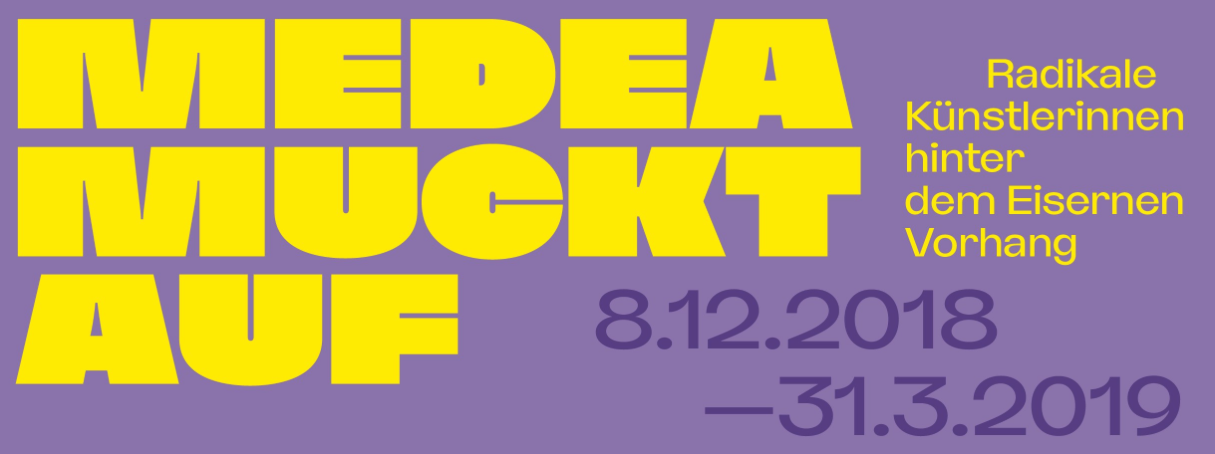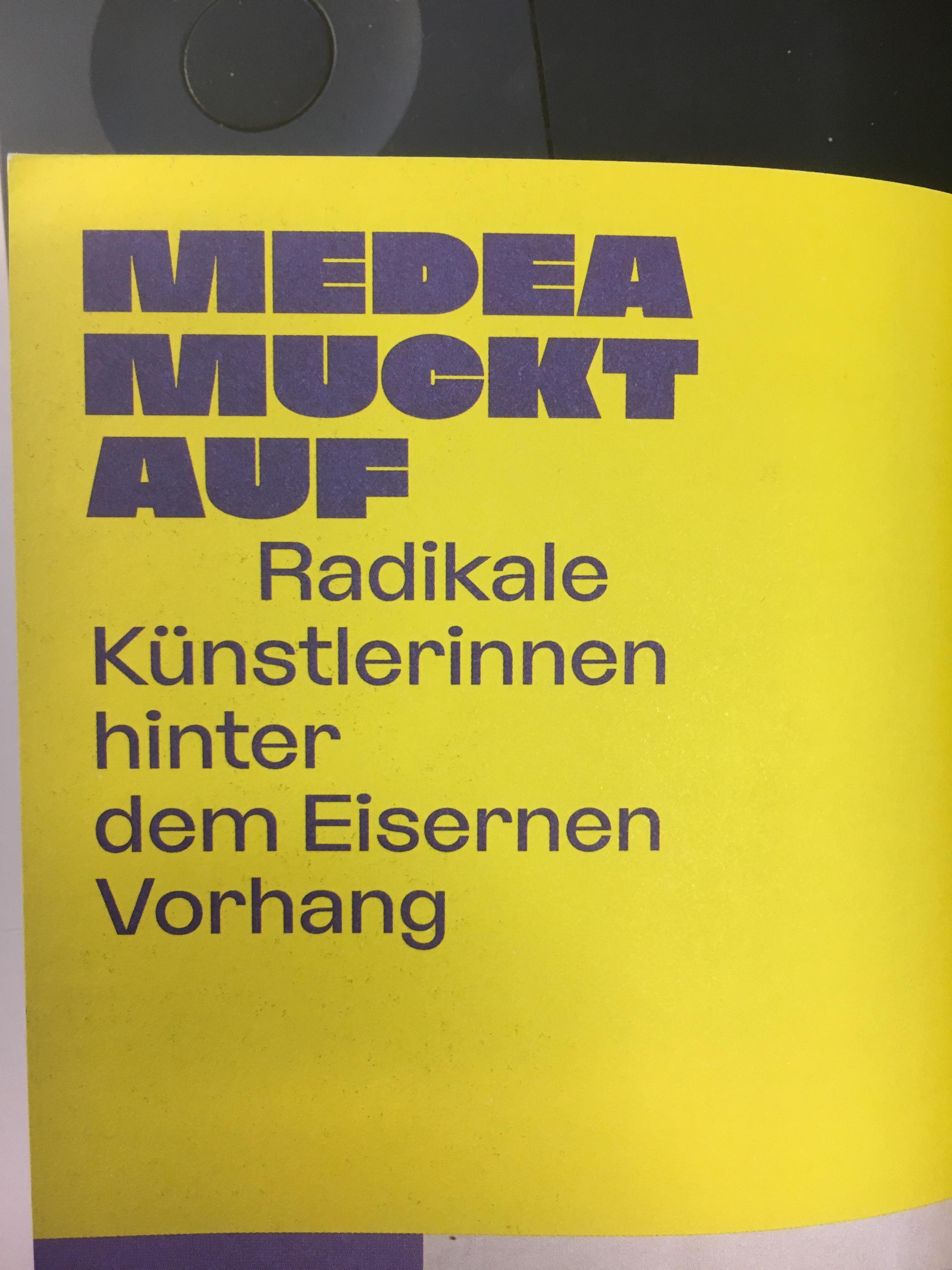
Suche Schrift Flyer Staatliche Kunstsammlung Dresden
ich suche diese beiden tollen Schriften, die ich auf einen Fyler für eine Ausstellung entdeckt habe.
Spontan musste ich an die Sharp Grotesk denken, aber nur der Schnitt Black 25 geht ansatzweise in die Richtung.
Vielleicht mal bei den Kunstsammlungen nach den Designern fragen und diese bzgl. Font kontaktieren?